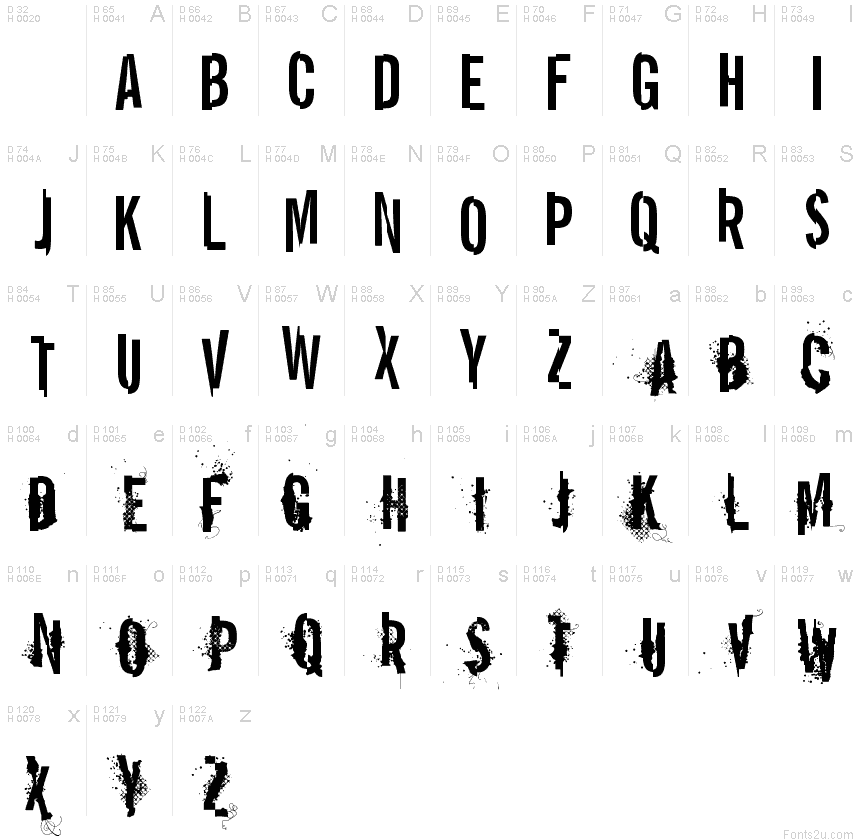
VTKS Report Error to darmowy, erodowany font grunge typu display autorstwa Douglasa Vitkauskasa, który stawia na efekt zniszczonego druku. Wielkie litery sprawiają wrażenie poszarpanych, zachlapanych i na wpół skorodowanych. Połączenie surowych brył, efektów rozpryskanej farby i brakujących fragmentów sprawia, że cały krój wygląda bardziej jak plakat zerwany ze ściany niż jak sterylny projekt cyfrowy.
Świetnie sprawdzi się na ulotkach klubowych, okładkach zinów, grafikach protestacyjnych, w tytułach horrorów i wszędzie tam, gdzie potrzebujesz brudu, szumu i kontrolowanego chaosu. Wykorzystaj go w krótkich nagłówkach, okładkach czy monogramach, jeśli chcesz, aby same litery budowały nastrój dzięki swoim postrzępionym krawędziom i rozsypanym fragmentom.